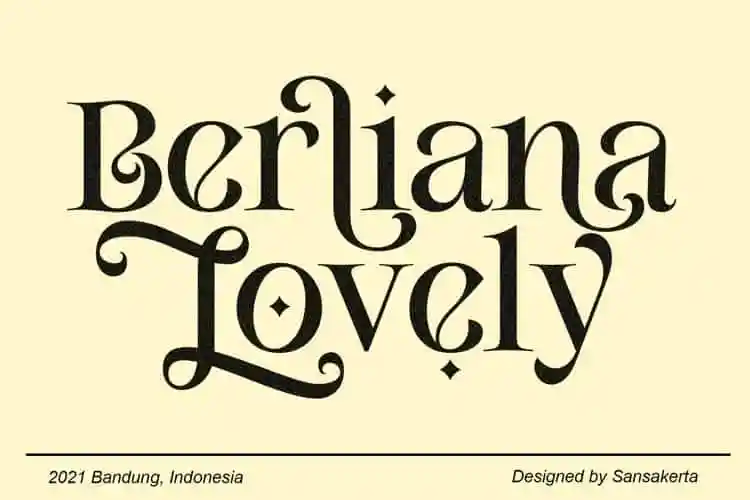
Berliana Lovely Serif Font – Download Grátis
Berliana Lovely Serif é uma elegante tipografia serif que se destaca por suas ligaturas originais com grandes variações e um vasto número de alternativas sofisticadas. Uma das características mais destacáveis desta fonte são as belas ligaturas, que oferecem à designer a capacidade de criar design moderno ou vintage. O suporte multilíngue e o auxílio do Estilo Estético permitem ao designer adaptar o texto para qualquer linguagem. Esta font é extremamente versátil, sendo perfeitamente adequada tanto para textos grandes quanto pequenos. Suas particularidades fazem dela uma excelente opção para projetos de marca, criação de logotipos, embalagens de roupas, cabeçalhos de revistas ou simplesmente como um overlay de texto estilizado sobre qualquer imagem de fundo. Com Berliana Lovely Serif, a criatividade do designer tem limites apenas em sua imaginação.